図には2種類の「ちまた」という字を並べてみました。皆さん、なじみのある字はどちらでしょうか? 辞書に載っているのは、左のほうです。右は、一時期コンピュータでよく見られた形で、そのころは一部の雑誌や書籍でもこちらの形が使われていましたが、今ではもう、あまり見かけることはなくなりました。
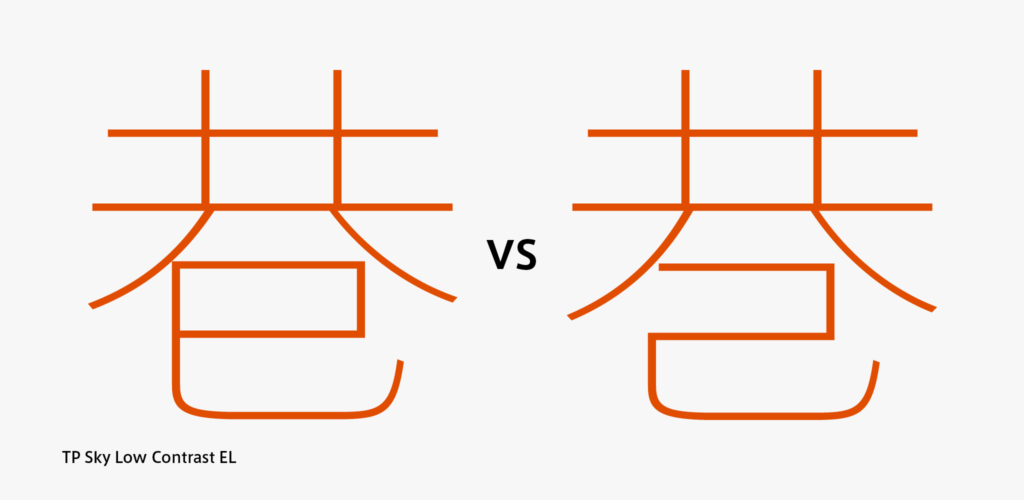
現在タイププロジェクトが提供している日本語フォントは「AXIS Font ProN」「TP明朝 StdN」のように、名前に「N」が付いています。このように「N」が付いているフォントでは、「ちまた」と入力して変換すると、左側の字体が表示されるはずです。右側の字体を表示したい場合「JIS83字形(jp83)」または「JIS90字形(jp90)」というOpenTypeフィーチャーを使ってグリフを置き換えます。
このシリーズでは、これまで「グリフの位置を調整する」GPOSフィーチャーについて説明してきました。今回から「グリフを置き換える」GSUBフィーチャーを紹介していきます。